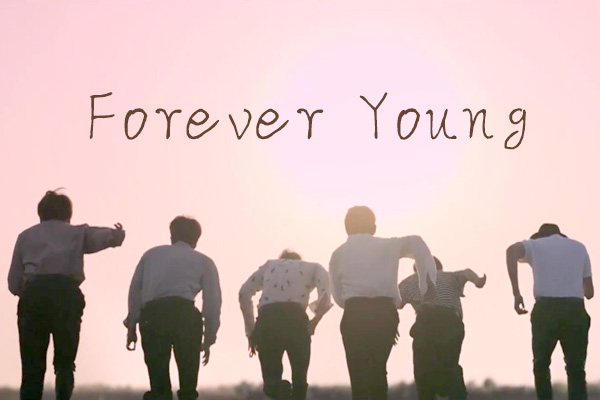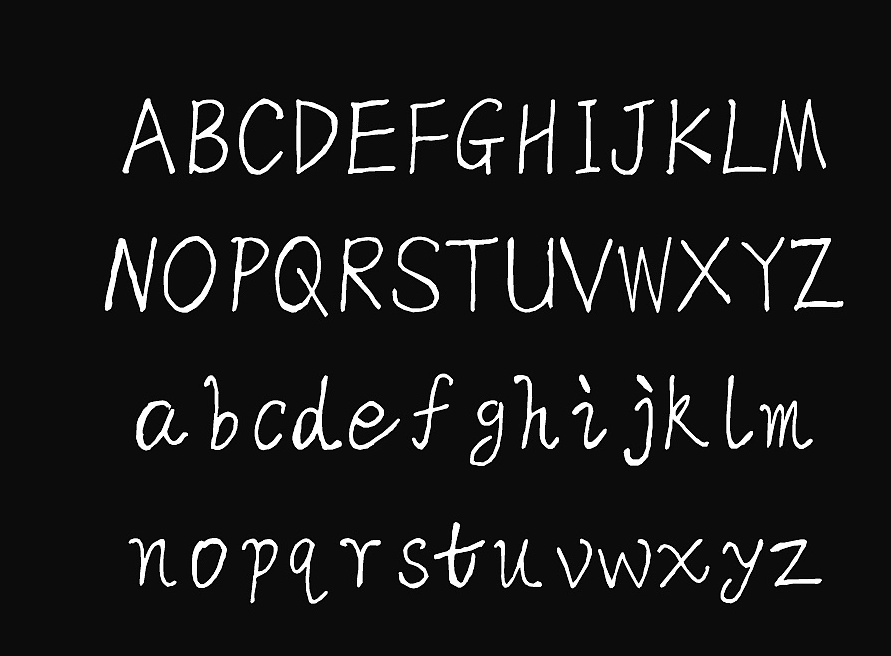
智勇手书体-英文版
由设计师 Joker9 倾力打造,ZhiyongWrite(智勇手书英文体)这款英文字体以其独特的手写风格在字体界独树一帜。其风格自然、流畅,尽显设计师的匠心独运。更难能可贵的是,这款字体完全免费商用,为您的各类设计需求提供了强有力的支持。
无论是作为英文正文字体,还是与其他免费字体手书体搭配使用,ZhiyongWrite都能展现出其优雅而富有特色的风格。其手写风格给人一种亲切而自然的感觉,使文字更具有情感和温度。同时,其多样化的字重设计也使其能够适应各种不同的排版需求。